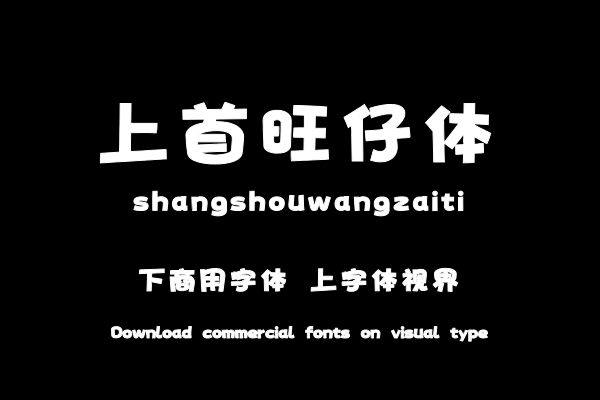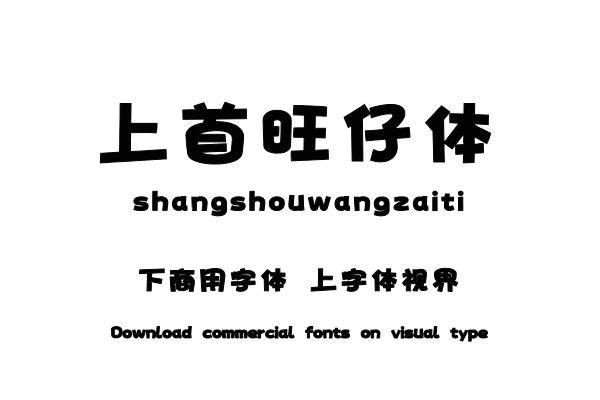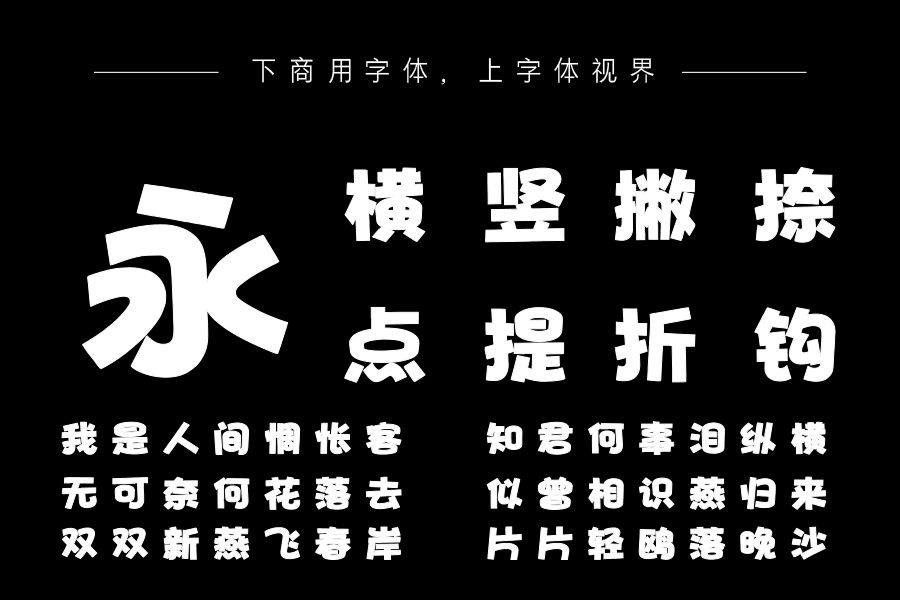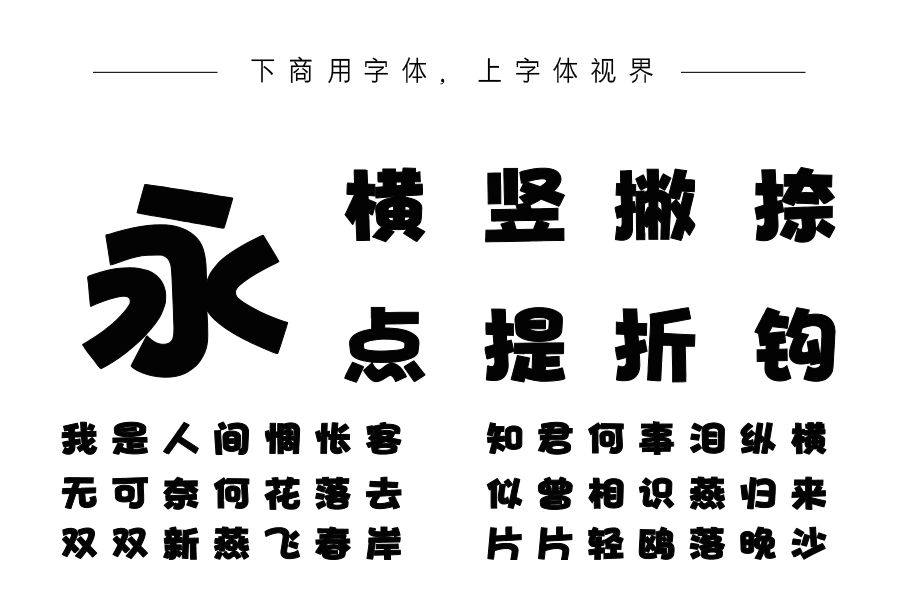
上首旺仔体,充满童趣和生命力字体。不遵循传统字体的规范,通过变形使文字更加生动活泼,创造出新颖有趣的视觉效果。购买须知:“下载服务费”与“字体VIP”所获得字体 仅用于个人非商用, 商用请联系付费授权。本字体为电脑用字,手机没有root权限不支持直接手机换字(手机如何root,请自行百度搜索教程)。购买前请先 了解清楚后再付款 ,字体为虚拟产品无法回收 一旦购买不支持退款。